Вертикальное многоточие ⋮ в рукописном шрифте: как отличить знак от кнопки меню
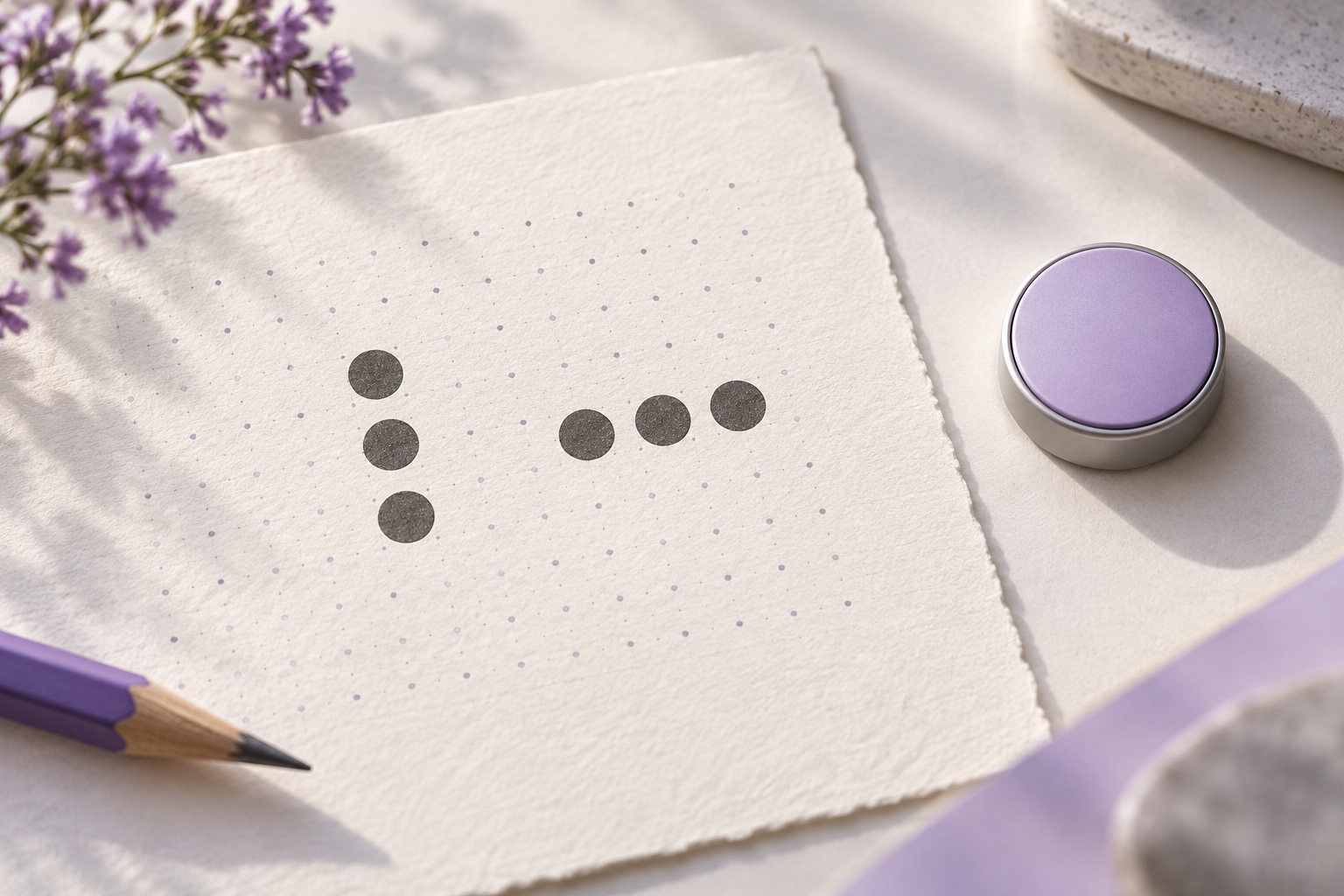
Вертикальное многоточие ⋮ легко принять за обычный значок меню: в обоих случаях видны три точки одна под другой. Но в шрифте важен не только рисунок — сначала нужно понять, будет ли знак частью текста, математической записи или управляющей кнопкой интерфейса. Разберём, как подготовить его глиф, проверить кодовую точку и не обещать пользователю неподходящее применение.
Сначала определите, какой именно знак нужен
Похожая на три вертикально поставленные точки форма встречается в нескольких задачах. В формулах и матричной записи U+22EE VERTICAL ELLIPSIS обозначает пропуск строк или элементов в вертикальном направлении. В интерфейсе похожая форма часто служит кнопкой дополнительных действий. В вертикальном наборе может понадобиться вертикальный вариант горизонтального многоточия. Визуальное сходство не делает эти применения взаимозаменяемыми: знак, смысл и поведение задаёт контекст.
До рисования запишите ожидаемый пример целиком. Для математического текста подойдёт фрагмент с несколькими строками матрицы и знаком между ними. Для интерфейса укажите, что находится в строке списка, где размещена кнопка и что она делает. Для вертикального набора покажите ориентацию всего фрагмента. Такая мини-спецификация заранее выявляет, нужен ли отдельный символ в шрифте или иконка, которую рисует компонент интерфейса.
Не смешивайте символ и его применение. Unicode называет U+22EE вертикальным многоточием и относит его к специальным знакам пропуска строк и столбцов матрицы. В веб-интерфейсе «три точки» обычно являются пиктограммой действия с доступным именем, а не текстовым знаком. Если продукту нужна кнопка, проектируйте кнопку и её семантику отдельно; наличие глифа в гарнитуре не создаёт доступную интерактивную область.
U+22EE, U+2026 и U+FE19: похожий силуэт, разные случаи
U+2026 … — обычное горизонтальное многоточие для текста. Unicode описывает его как знак, которым обозначают недосказанность или пропуск; в математической записи существуют отдельные варианты, включая U+22EE ⋮ для вертикального пропуска строк. U+FE19 ︙ — совместимый презентационный знак для вертикального отображения горизонтального многоточия. Это не повод подставлять один код за другой: прежде всего смотрите на язык, направление набора и назначение фрагмента.
Для цифрового рукописного шрифта практическая развилка проста. Если гарнитура должна поддерживать математические выражения и набор использует вертикальный пропуск строк, проверьте покрытие U+22EE. Если проект отображает обычный текст вертикально, разберитесь, поддерживает ли приложение вертикальные варианты глифов; Unicode рекомендует механизм замены варианта, например OpenType vert, когда он доступен. Совместимый U+FE19 относится к конкретному сценарию отображения и кодировочной совместимости, а не к универсальной кнопке меню.
Для кнопки «ещё» правильнее использовать библиотеку иконок или специально спроектированный UI-глиф, если именно так устроен продукт. Это позволяет управлять размером области нажатия, фокусом, контрастом и альтернативным названием независимо от выбранного шрифта. Рукописная гарнитура может повлиять на соседний текст, но не должна быть единственным источником значка, если интерфейс обещает единообразное поведение на платформах.
Как спроектировать три точки, чтобы они читались
Начните с трёх одинаковых по массе точек, расположенных по общей вертикальной оси. Для рукописной манеры допустимы небольшие оптические различия, но форма должна восприниматься как регулярная последовательность, а не как россыпь случайных следов. Сравните знак с точкой, двоеточием и горизонтальным многоточием этой же гарнитуры: толщина штриха, округлость концов и степень живости должны выглядеть родственными, а расстояния между элементами оставаться достаточными для уверенного считывания.
Оптическое центрирование важнее механического. Если точки нарисованы круглыми, геометрический центр обычно понятен; если это живые мазки, у каждой может быть смещён визуальный вес. Смотрите на знак в реальном окружении, например между двумя строками матрицы или рядом с подписью списка. Не привязывайте вертикальный центр только к строчной высоте: конкретная гарнитура может использовать другие пропорции, и знак должен оставаться различимым рядом с цифрами, прописными буквами и математическими операторами.
Не превращайте вертикальное многоточие в три крошечных кружка, если рабочий размер делает их похожими на дефект сканирования. И наоборот, чрезмерно крупные точки могут выглядеть как декоративный разделитель. В handwritten-проекте исходные точки иногда получаются неодинаковыми, поэтому полезно выбрать повторяемый образец из алфавита и заново нарисовать символ, а не копировать случайные следы с шаблона. В цифровом контуре удобно проверить общую ось и интервалы направляющими, затем убрать ощущение механической стерильности на итоговом размере.
Ширина, метрики и соседние знаки
У символа должна быть ширина, согласованная с его ролью. Математический знак в строке формулы не должен вторгаться в соседние элементы или создавать лишнюю пустоту; отдельная UI-иконка может центрироваться внутри контейнера, и её визуальная ширина не обязана совпадать с метрикой текстового глифа. Эти два случая нельзя тестировать одной меркой. В шрифте проверьте боковые поля относительно цифр и круглых скобок; в интерфейсе отдельно оцените фактический размер пиктограммы и область действия кнопки.
Вертикальное многоточие требует сначала разобраться в смысле, затем рисовать форму. Для матричного пропуска проверьте U+22EE и включение глифа в экспорт; для вертикально набранного текста учитывайте поведение движка; для меню проектируйте полноценную иконку и кнопку. Подготовьте тестовую строку, проверьте размер и fallback, а затем включайте символ в шрифт только под подтверждённый сценарий. Для собственного рукописного набора Fontgenerator помогает пройти путь от шаблона к проверяемому файлу, а набор редких знаков можно планировать заранее.